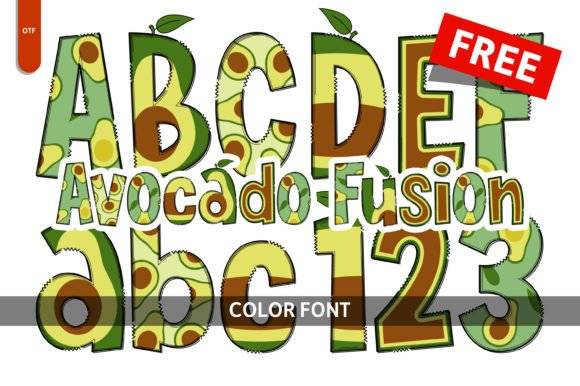
Fuente Avocado Fusion para titulares, carteles y proyectos de marca
Dale un toque de fantasía a tus diseños con la fuente gratuita Avocado Fusion . Perfecta para proyectos lúdicos o artísticos, brilla en libros infantiles, pósteres, invitaciones y tarjetas de felicitación.
- Estilo atrevido y artístico
- Ideal para diseños divertidos.
- Se utiliza en libros y carteles infantiles.
Crea diseños atractivos y divertidos con la fuente gratuita Avocado Fusion, tu opción ideal para agregar un toque divertido.